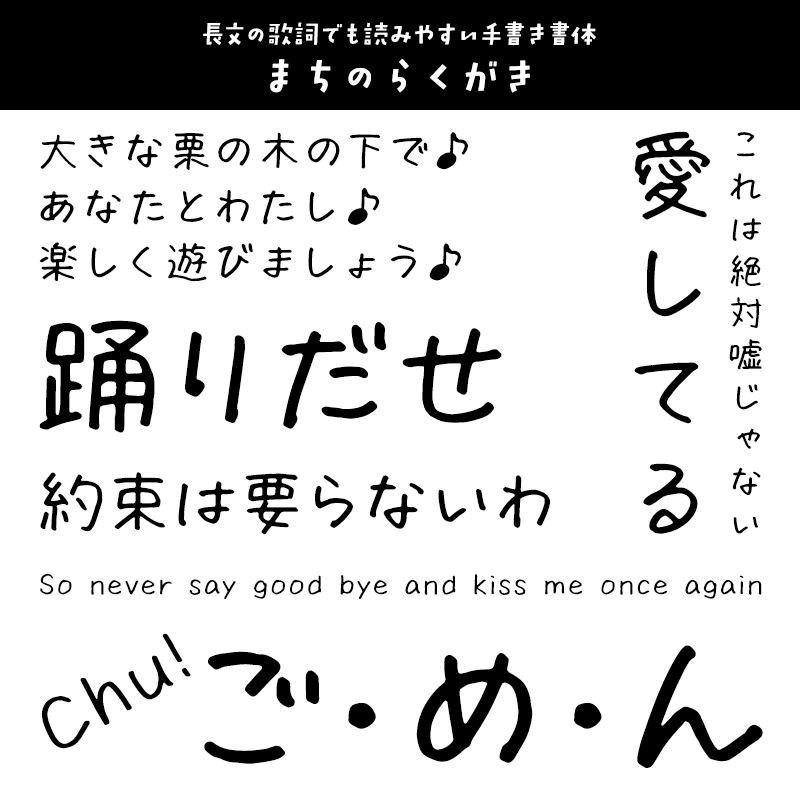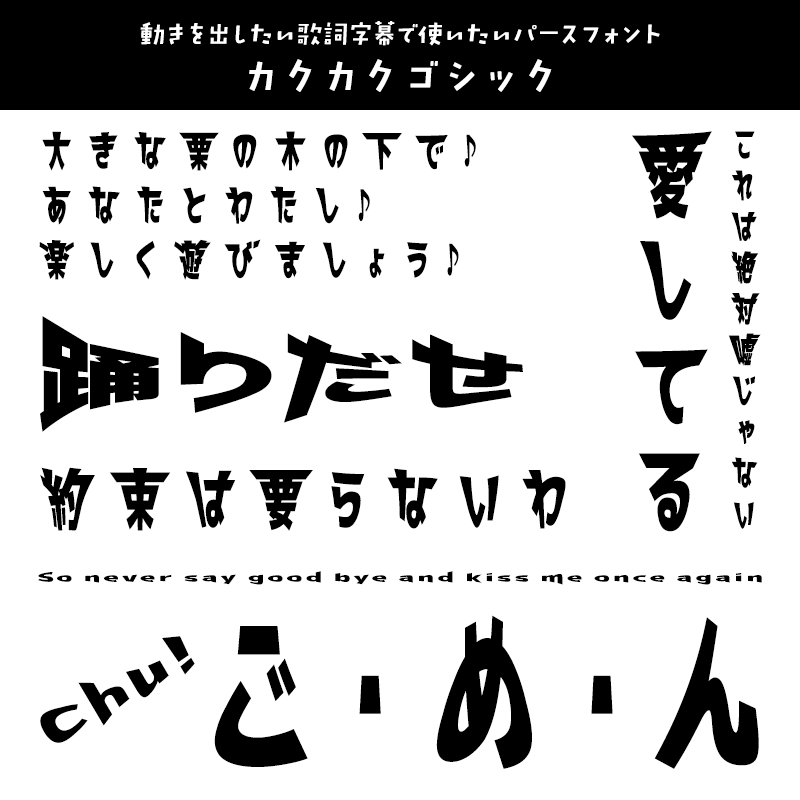
「歌詞字幕」に合うフォント:特化型 目的別フォントガイド #173
「歌詞字幕」に合うフォントをスタッフが選びました
「歌詞字幕」に合うフォント りいクッキー
ポップで明るい楽曲の歌詞字幕におすすめ
りいクッキー【りいのフォント】
「歌詞字幕」に合うフォント りいクッキー
楽しく個性的なデザインで、使うだけでポップな雰囲気に。レギュラーRはしっかりとした太さで見出しやタイトルにぴったり。ライトLは細めで、ナチュラルな雰囲気を演出できます。
「歌詞字幕」に合うフォント 藍原筆文字隷書
和風・古風の楽曲にぴったりな手書きの隷書体
藍原筆文字隷書【Faraway】
「歌詞字幕」に合うフォント 藍原筆文字隷書
和風や中華風のデザインにぴったりの古風なフォント『藍原筆文字隷書』は書道歴20年以上の藍原彼方が手書きした文字を元に作成したフォントです。
「歌詞字幕」に合うフォント かもめ明朝
やわらかい印象が歌詞字幕に合うレトロ系明朝体
かもめ明朝【文字魚/Typographish】
「歌詞字幕」に合うフォント かもめ明朝
「かもめ明朝」は築地四号系で昭和初期に作られたであろう金属活字から着想を得て作られました。初作の「築豊明朝」はシャープさと透明感を意識したのに対し、「かもめ明朝」は金属活字特有の文字のふくよかさを強調してやわらくて、温かみのある印象になっています。
「歌詞字幕」に合うフォント まちのらくがき
長文の歌詞でも読みやすい手書き書体
まちのらくがき【まち@machicooooo】
「歌詞字幕」に合うフォント まちのらくがき
サインペンで書いたゆるい手書き。それでいて長文でも読みやすい。そんなフォントを目指して作成しました。
「歌詞字幕」に合うフォント 花間影体
歌詞字幕として動画になじむ素朴な手書き風書体
花間影体【楽フォント】
「歌詞字幕」に合うフォント 花間影体
素朴な線幅と、わずかにざらついた質感を持つ手書き風の書体です。全体的に素朴で親しみやすい雰囲気があり、やや左に傾いた字形が視覚的な美しさとバランスの良い文字組みを実現します。
「歌詞字幕」に合うフォント カクカクゴシック
動きを出したい歌詞字幕で使いたいパースフォント
カクカクゴシック【にっぽり】
「歌詞字幕」に合うフォント カクカクゴシック
上下左右にパースのかかった書体です。立体的な表現によって勢いやスピード感を演出します。
「歌詞字幕」に合うフォント DFシネマ凜 W4
字幕師の手書き文字をもとにした感情表現豊かなフォント
DFシネマ凜 W4【ダイナフォント】
「歌詞字幕」に合うフォント DFシネマ凜 W4
長年、映画などの字幕を手掛けてきた字幕師の手書き文字を基に開発した字幕書体です。字幕師本人が書いた手書き文字の個性を最大限に活かし、躍動感を感じさせる感情表現豊かな書体になっています。
「歌詞字幕」に合うフォント ミウラ見出しLinerOtf R
かわいらしい印象を与えてくれる手書き風書体
ミウラ見出しLinerOtf R【ミウラフォント/モップスタジオ】
「歌詞字幕」に合うフォント ミウラ見出しLinerOtf R
手書き文字らしさを生かすために全ての文字を可変幅(プロポーショナル)で作成した特殊なフォント。「ぐちゃっ」とした書き直し筆跡など、オリジナルの記号も魅力です。
「歌詞字幕」に合うフォント 桜と少女体
メッセージ性の高い歌詞字幕にぴったりな手書き風フォント
桜と少女体【楽フォント】
「歌詞字幕」に合うフォント こまどり+
ゆったりした気分で、つるつるした紙に細い平筆で描かれた書体。メリハリがあり、字が右上に傾いてすっきりとしています。息をしている間に自由な感覚が生まれてくるような視覚表現力があります。
「歌詞字幕」に合うフォント 花とちょうちょ
手書きの歌詞風に仕上がり、メッセージ性が増します
花とちょうちょ【鈴木メモ】
「歌詞字幕」に合うフォント 花とちょうちょ
ペンで右上がりに書いた手書き文字から作った、ちょうちょのように軽やかな日本語フォント。手書きの歌詞風に仕上がりメッセージ性が増します。
「歌詞字幕」に合うフォント 空とひこうき
インクのにじみやラフな抜け感が爽やかな青春ソングに
空とひこうき【鈴木メモ】
「歌詞字幕」に合うフォント 空とひこうき
「空とひこうき」は、空に長く伸びてゆくひこうき雲をイメージした書体で、万年筆でさらりと書いたようなインクのにじみやラフな抜け感が特徴があり。歌詞やカジュアルな手紙文などにも使えそうです。
「歌詞字幕」に合うフォント TMミモザStdN
大人女子なメッセージのアピールに
TMミモザStdN【タンデムフォント】
「歌詞字幕」に合うフォント TMミモザStdN
ペンのにじみを残した、自然で穏やかな女性の手書き文字です。特典収録の装飾素材も大人女子感いっぱいで使いえます!
「歌詞字幕」に合うフォント JTC淡斎古印体「歌」
底知れぬ不安感が漂う歌詞にピッタリ!
JTC淡斎古印体「歌」【ニィスフォント】
「歌詞字幕」に合うフォント JTC淡斎古印体「歌」
歌詞動画以外にも、サムネイル・タイトルやPOP広告など、幅広い用途で活躍するフォントです。
「歌詞字幕」に合うフォント HG創英イオリ書体
少しクセのある手書き風デザイン書体
HG創英イオリ書体【リコー】
「歌詞字幕」に合うフォント HG創英イオリ書体
少しクセのある手書き風デザイン書体です。主張したい歌詞にピッタリです。
「歌詞字幕」に合うフォント モトヤアネモネ3
歌詞の世界観を表現する、叙情感たっぷりなフォント
モトヤアネモネ3【モトヤ】
「歌詞字幕」に合うフォント モトヤアネモネ3
叙情感たっぷりなフォントです。淡い、切ない、儚い、などフォントひとつで歌詞の世界観を表してくれます。
「歌詞字幕」に合うフォント 風来坊書体
シュフノミチのMVでも使用されている「和モダン」なフォント
風来坊書体【昭和書体】
「歌詞字幕」に合うフォント 風来坊書体
その名のイメージを基に作製された、従来の昭和書体にはないPOP調の字形、「和モダン」の趣を演出します。シュフノミチのMVでも使用されているフォントです。
「歌詞字幕」に合うフォント 姫筆フォントシリーズ 伴書体-詩-
ミステリアスな歌詞にピッタリな個性的なフォント
姫筆フォントシリーズ 伴書体-詩- 【Design筆文字Font】
「歌詞字幕」に合うフォント 姫筆フォントシリーズ 伴書体-詩-
実直で素朴なラインと熟考されたフォルムが絶妙なデザイン毛筆!
「歌詞字幕」に合うフォント DSサラ
すっきりあっさり字幕に使いやすいフォント
DSサラ【七種泰史/デザインシグナル】
「歌詞字幕」に合うフォント DSサラ
さらりサラサラ。すっきり、あっさり味の書体です。
「歌詞字幕」に合うフォント イワタ福まるごカタル R